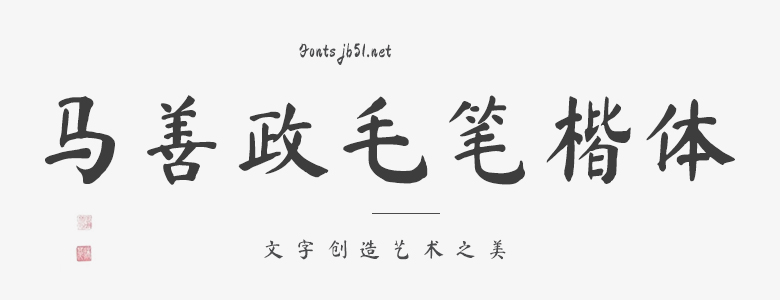
馬善政毛筆楷體是一款精心設(shè)計(jì)的毛筆楷體字體,它的特點(diǎn)是將傳統(tǒng)毛筆書法的韻味與現(xiàn)代字體設(shè)計(jì)相結(jié)合,呈現(xiàn)出一種既古樸又現(xiàn)代的風(fēng)格。該字體的每個(gè)字形都經(jīng)過精心的手寫設(shè)計(jì),使用了飽滿、富有張力的線條和筆畫,使得字體看起來既有力度又有柔韌性。 馬善政毛筆楷體的字形結(jié)構(gòu)嚴(yán)謹(jǐn)、平穩(wěn),筆畫粗細(xì)得當(dāng),視覺效果舒適自然。在閱讀時(shí),字體流暢自然,視覺舒適,不易產(chǎn)生疲勞感。此外,該字體還具有良好的可讀性,適用于各種印刷、廣告、設(shè)計(jì)等場合,可以滿足不同用戶的需求。 總的來說,馬善政毛筆楷體是一款既具有傳統(tǒng)毛筆書法的韻味,又不失現(xiàn)代感的優(yōu)秀字體,它不僅適合用于正式場合的文書處理,也可以用于具有文化氣息的宣傳、廣告等設(shè)計(jì)作品。